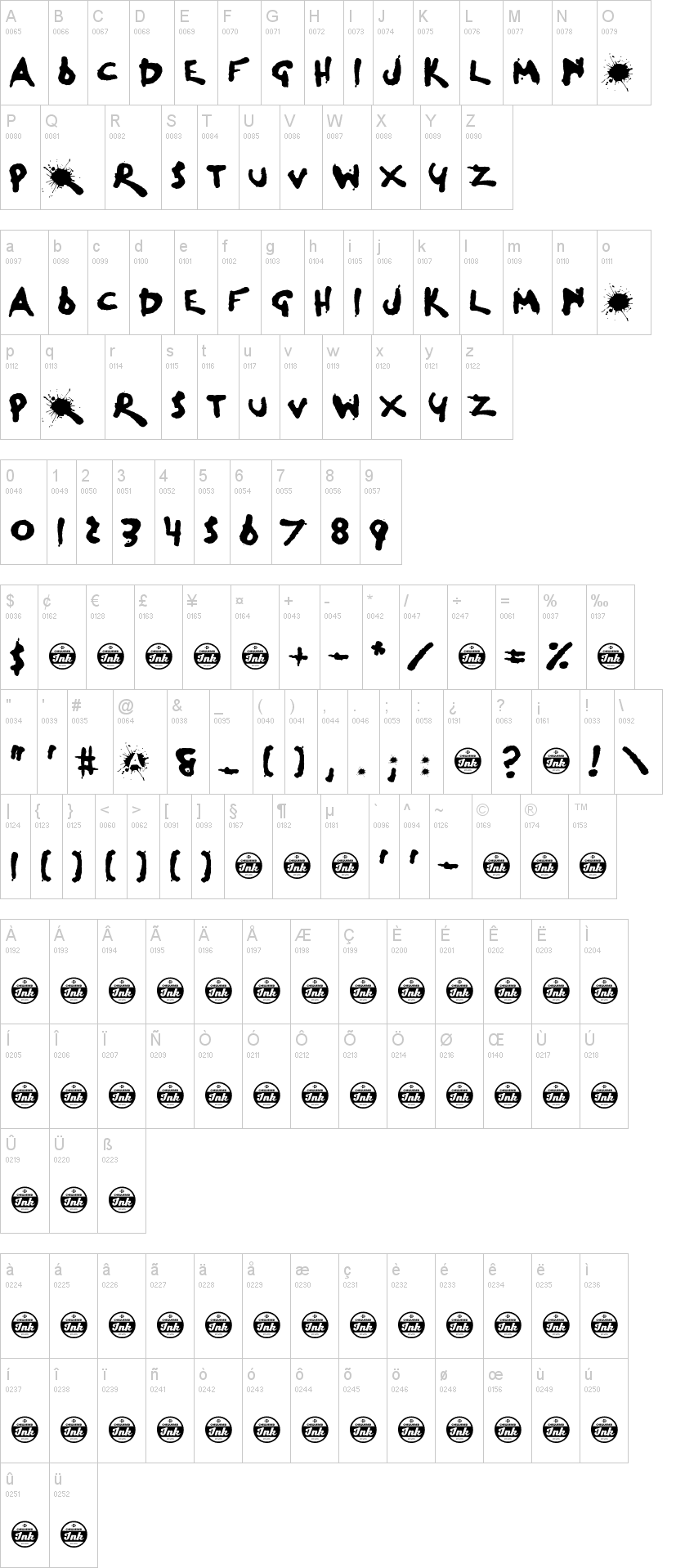
? Dog Rough 是一款由英国设计师Rob Clarke设计的字体。它是一款粗体字体,带有独特的技术感,让字体看起来更加有力。它的特点是它的曲线更加流畅,给人以粗犷而又柔和的感觉,具有独特的视觉效果。Dog Rough字体可以用于各种场景,如标题、广告、海报、T恤等。内容介绍
Dog Rough是一款非常不错的手写艺术字体,具有很好的视觉感,适合于文化类的宣传设计、商业类品牌的广告和产品包装设计以及个性化文字排版等较多场景。